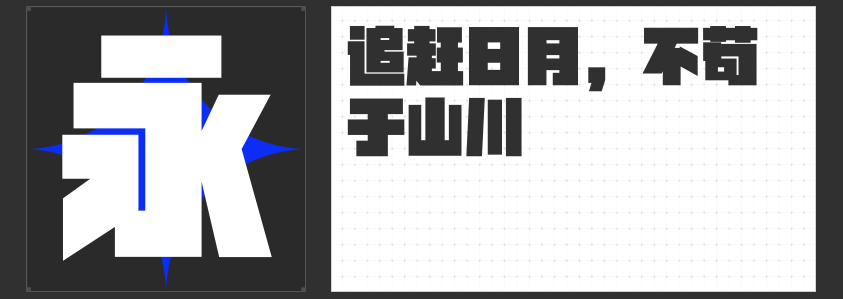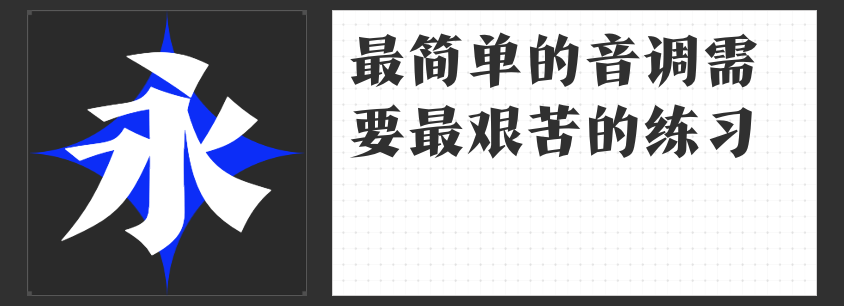
四款精品字体推荐:解锁海报设计的视觉张力
在海报设计的世界里,字体不仅是信息传递的载体,更是情感与风格的塑造者。以下四款独具特色的字体,以其独特的设计语言与艺术表现力,为海报创作注入鲜活的视觉能量。
一、造字侠磅礴简繁
这款字体以中正之姿承载丰富的感官层次,运笔节奏如乐章起伏,笔画粗细对比强烈,飞白处见功力,转折处方圆交融。其设计既保留传统书法的骨力,又融入现代审美中的动态平衡,适用于需要传递力量感与文化底蕴的宣传海报,如文化展览、历史题材活动等场景。
二、高手字斋树高行书
作为一款书法字体,高手字斋树高行书以连贯流畅的笔触诠释“气韵生动”。笔画间的牵丝映带自然天成,仿佛一笔挥就的即兴创作。这款字体尤其适合需要营造轻松氛围或强调人文情怀的海报设计,如音乐节、艺术沙龙等主题,其灵动性可瞬间拉近与观众的距离。
三、励字开拓者简 超特黑
以直线构建的方正字型打破传统黑体的沉闷感,中宫开阔、重心稳定的设计赋予文字雕塑般的视觉重量。去钩处理与竖直撇捺的创意,强化了字体的未来感与科技属性,是科技产品发布会、建筑展览等现代风格海报的理想选择,其简约外形下暗藏强烈的视觉冲击力。
四、高手字斋东京体
这款字体突破古典长形字结构,以方正均衡的块面重塑汉字形态。锋利笔触与光洁曲线的矛盾统一,既保证远距离的辨识度,又通过亲和的线条传递温暖感。适用于商业品牌宣传、城市文化推广等场景,尤其当需要平衡专业性与亲和力时,高手字斋东京体能以“外简内达”的设计哲学实现高效沟通。
每款字体都是设计师对汉字美学的深度解构与再创造,它们以不同的姿态回应着海报设计的核心命题——如何在有限空间内构建无限可能。选择适合的字体,即是选择与内容共鸣的视觉语言。